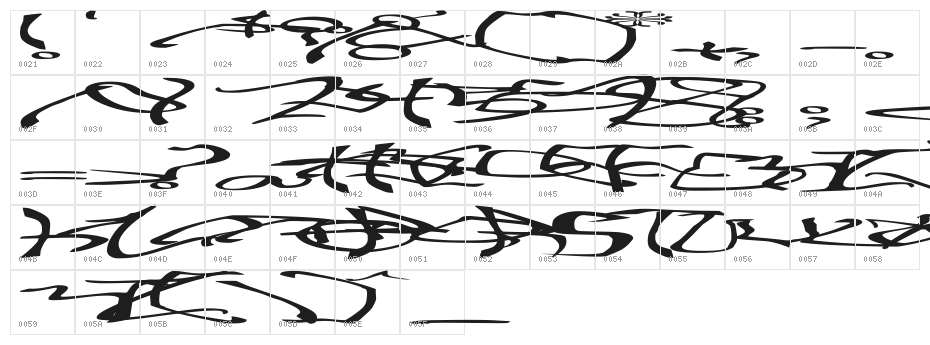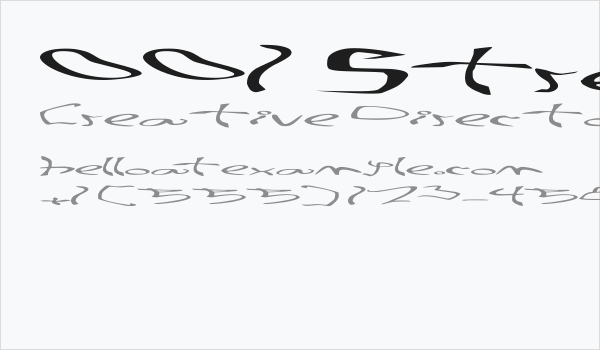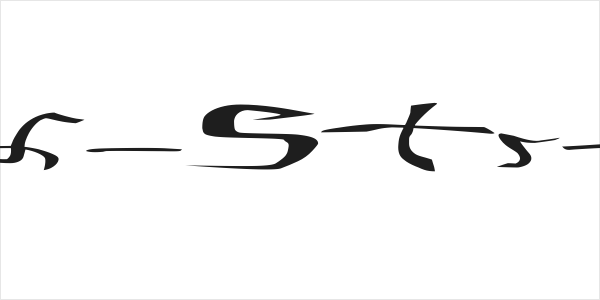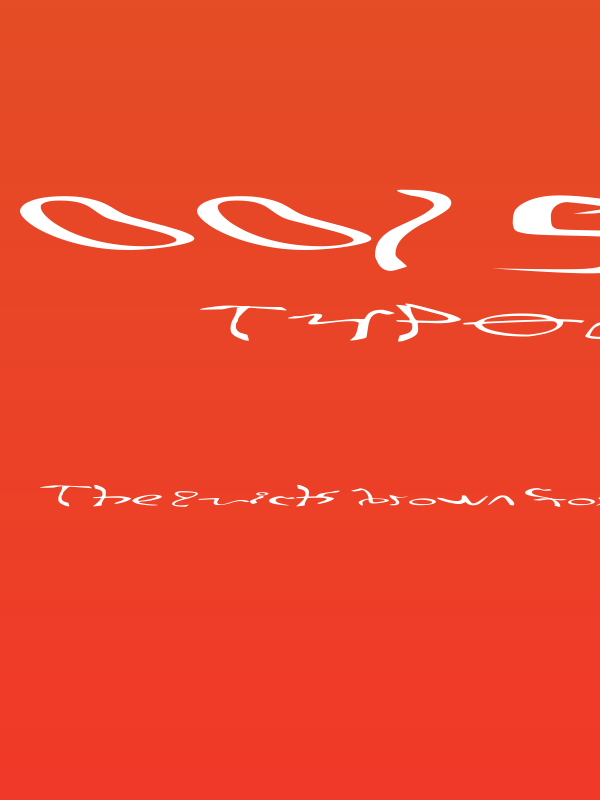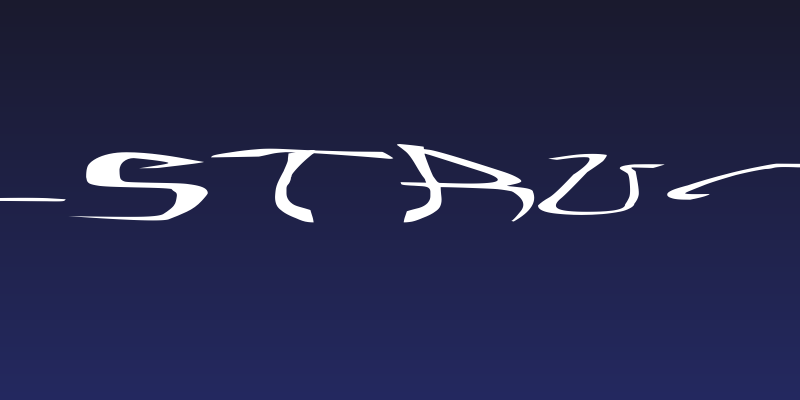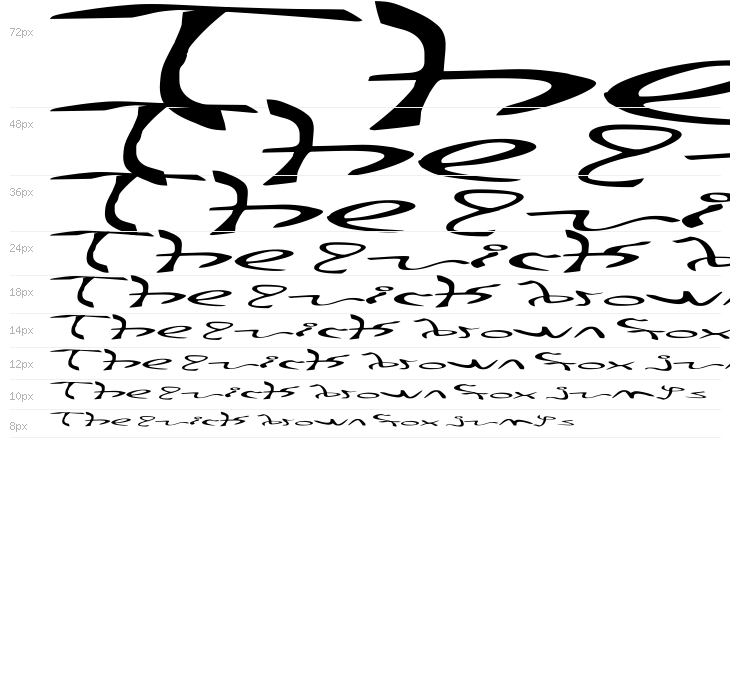
001 Stretched-Strung Very Wide Font
| Breite | Expanded |
| Anwendungsfall | Logos, Posters, Artistic Projects |
| Vorgeschlagene Projekte | Ideal for artistic projects, creative branding, unique posters, or any design work requiring a distinctive and unconventional typeface. |